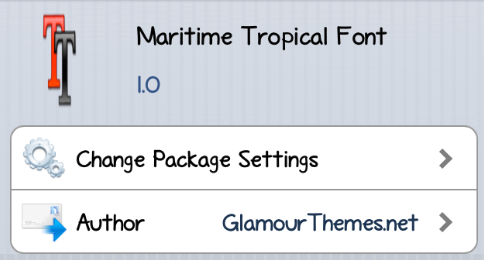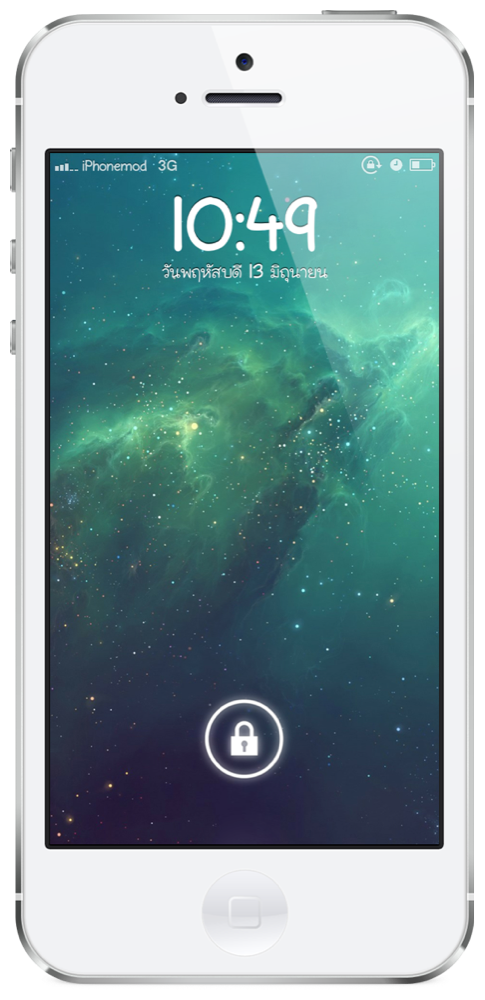
ก่อนหน้าได้แนะนำ ฟอนท์ไอโฟน – KG Payphone Font [Bytafont] หากว่าใครเบื่อแล้วก็มาชมตัวใหม่กันได้เลย แนวฟอนท์ที่ผมชอบจะออกไปทางการ์ตูนหน่อยๆ แต่ว่าต้องอ่านสะดวกด้วย มาลองตัวนี้ครับกับ Maritime Tropical Font จาก Bytafont
ผลงานที่ได้ครับ